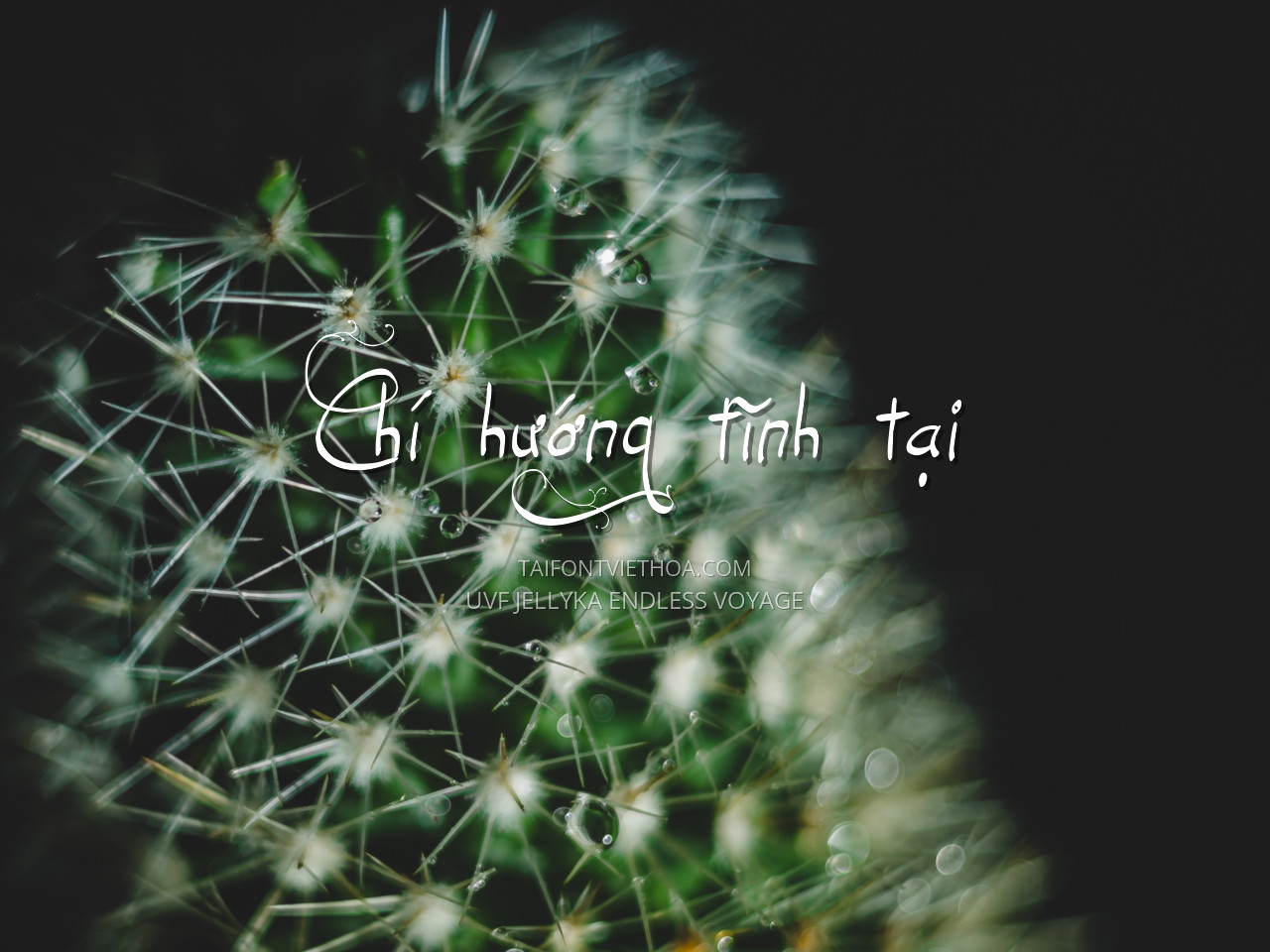
Font việt hóa UVF Jellyka Endless Voyage
Giới thiệu về font UVF Jellyka Endless Voyage
UVF Jellyka Endless Voyage là một kiểu chữ mang đậm phong cách chữ viết tay cổ điển kết hợp với hơi hướng gothic huyền bí. Được thiết kế như những nét mực phóng khoáng trên giấy da, font này gợi liên tưởng đến các bản viết tay từ thế kỷ trước hoặc nhật ký du hành bí ẩn. UVF Jellyka Endless Voyage được sưu tầm và chia sẻ bởi thành viên Font Chuẩn, đồng thời được taifontviethoa.com sử dụng trong nhiều dự án mang màu sắc cổ điển, kỳ bí hoặc mang tính cá nhân hóa cao.
Đặc điểm thiết kế và ứng dụng của UVF Jellyka Endless Voyage
Font có kết cấu handwritten với độ nghiêng rõ nét, các chữ cái bay bổng và nối liền như dòng mực thật. Một vài ký tự được cách điệu đầy sáng tạo, tạo cảm giác nghệ thuật và huyền bí. Font hỗ trợ tiếng Việt đầy đủ, rất thích hợp cho các thiết kế mang yếu tố cảm xúc hoặc vintage.
Ứng dụng lý tưởng: thiết kế thiệp mời sự kiện gothic, poster phim cổ trang, sản phẩm thủ công, bìa sách giả tưởng, hoặc branding mang phong cách cá nhân hóa độc đáo. Ngành nghề phù hợp: sự kiện văn hóa, nghệ thuật sáng tạo, xuất bản sách, thủ công mỹ nghệ và quảng bá cá nhân.